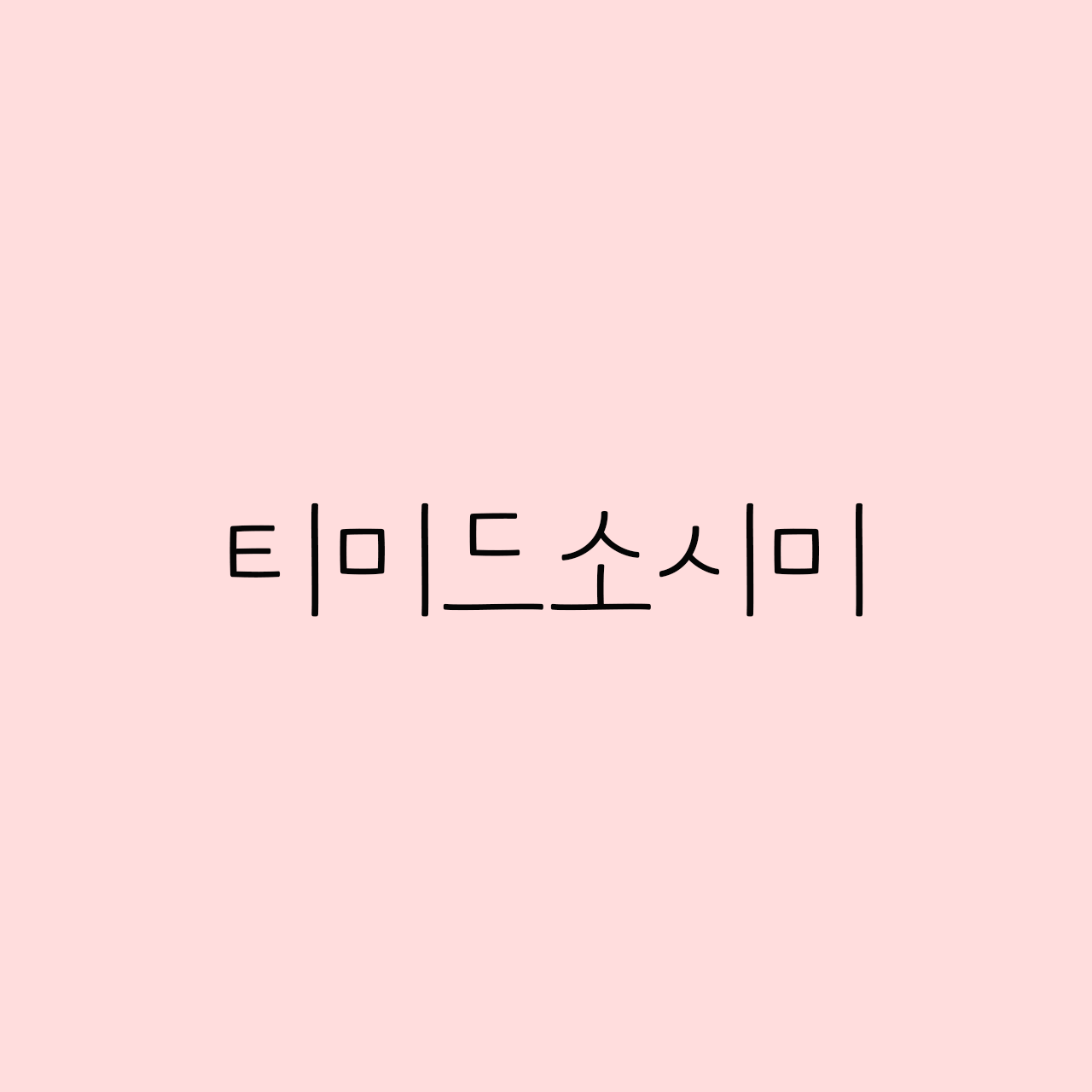
Dain 티미드소시미
5종 2023
초성의 크기가 작아 소심한 듯, 세심한 느낌을 주는 폰트입니다. 중성의 길이가 길어서 팔다리가 길고 넓은 어깨에 작은 얼굴과 작은 이목구비가 올망졸망 모여있는 느낌입니다. 감성적인 작업에 사용하시면 좋아요!
• Dain 티미드소시미 / Dain Timid
• 한글 11,172자 / 라틴 95자 / 약물 977자